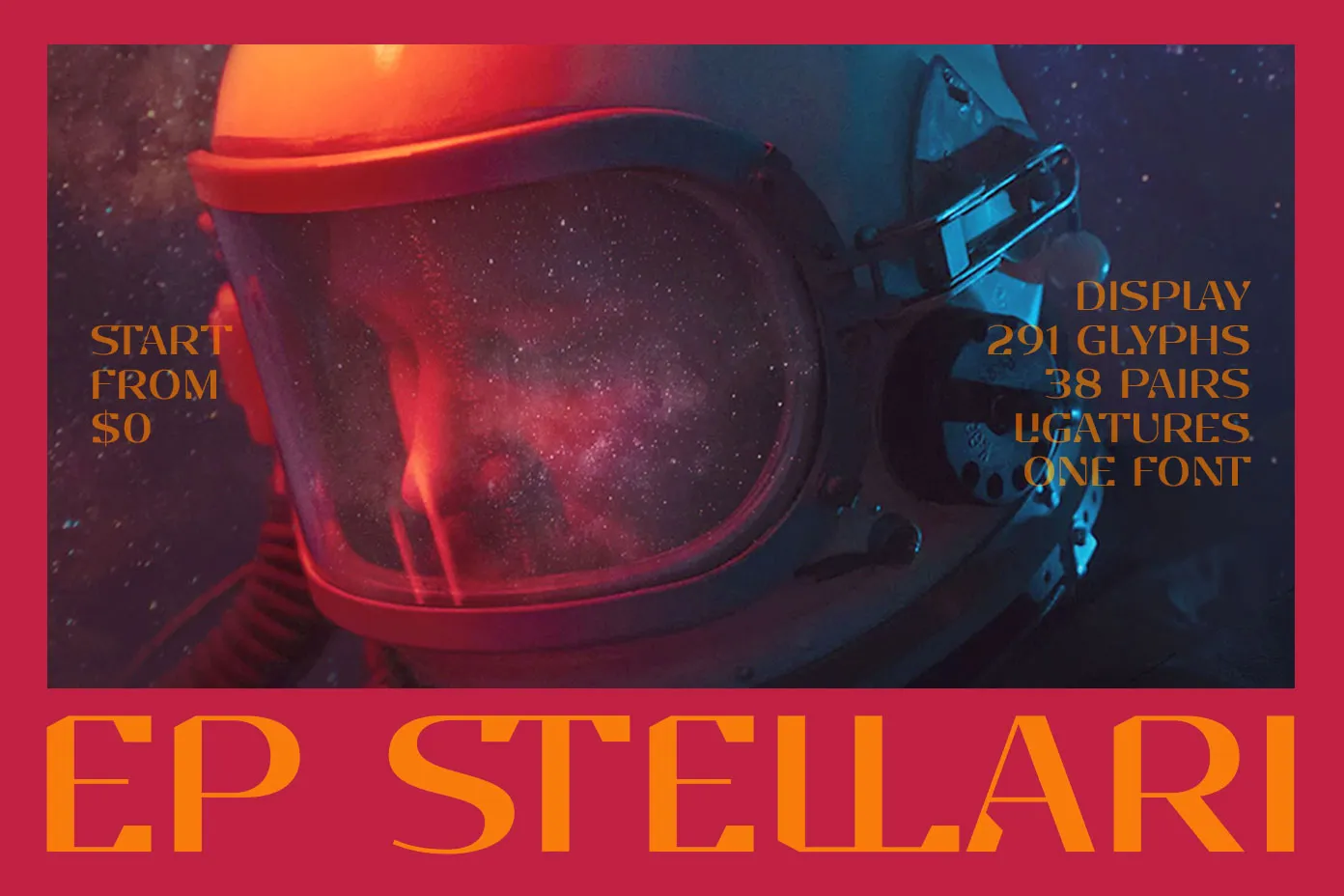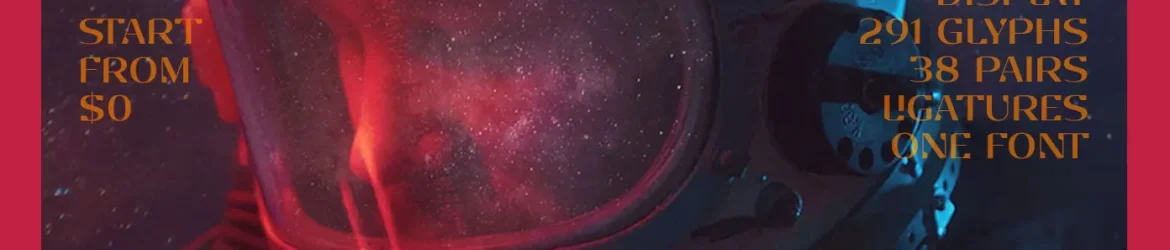
A fonte EP Stellari Font é uma peça de destaque para designers que buscam uma mistura única entre a modernidade futurista e a essência clássica. Desenvolvida pelo designer gnapyde, essa fonte se destaca com sua estrutura baseada na fusão de linhas grosas e finas, inspiradas em formas serifadas e formas futuristas robustas. Suas linhas, tanto grossas quanto finas, criam uma contraste interessante que dá ao texto um apelo visual dinâmico e moderno. Embora seu design seja essencialmente futurista, EP Stellari Font traz à superfície nuances clássicas que tornam o texto mais atraente e envolvente para uso em aplicativos digitais variados. Seja para criar um título empolgante em sua página web ou para destacar informações importantes em uma reportagem impressa, EP Stellari Font oferece a modernidade futurista necessária com os toques de sofisticação clássica que o designer gnapyde incorporou à fonte. Engajante e versátil, essa fonte é perfeita para quem busca um equilíbrio entre tendências contemporâneas e elementos tradicionais na composição visual de seus projetos.